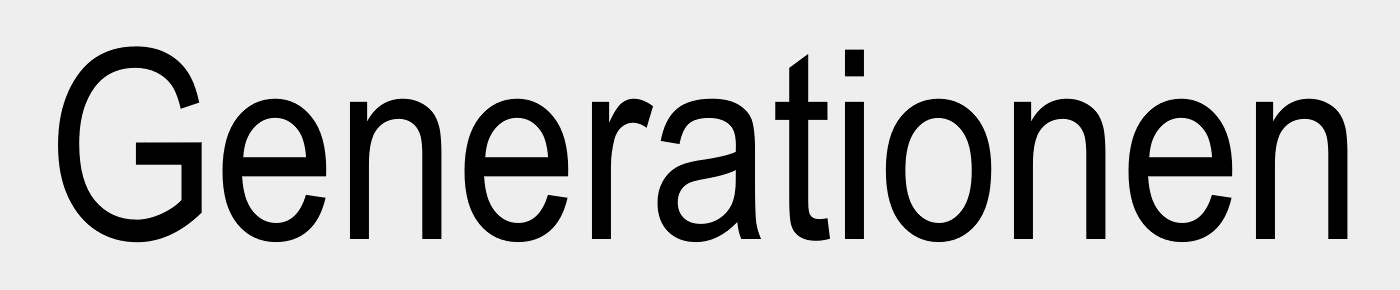
Welche Schriftart ist das?
Arial narrow.
Danke dir. Das dachte ich auch erst aber die Buchstaben von Arial Narrow sind etwas dünner und in fett sind sie zu dick.....
Das ist in deinem winzigen Beispiel nicht mit allerletzter Sicherheit zu sagen, ich bin mir aber zu 99,4723 % sicher.
Woher stammt dein Beispiel denn?